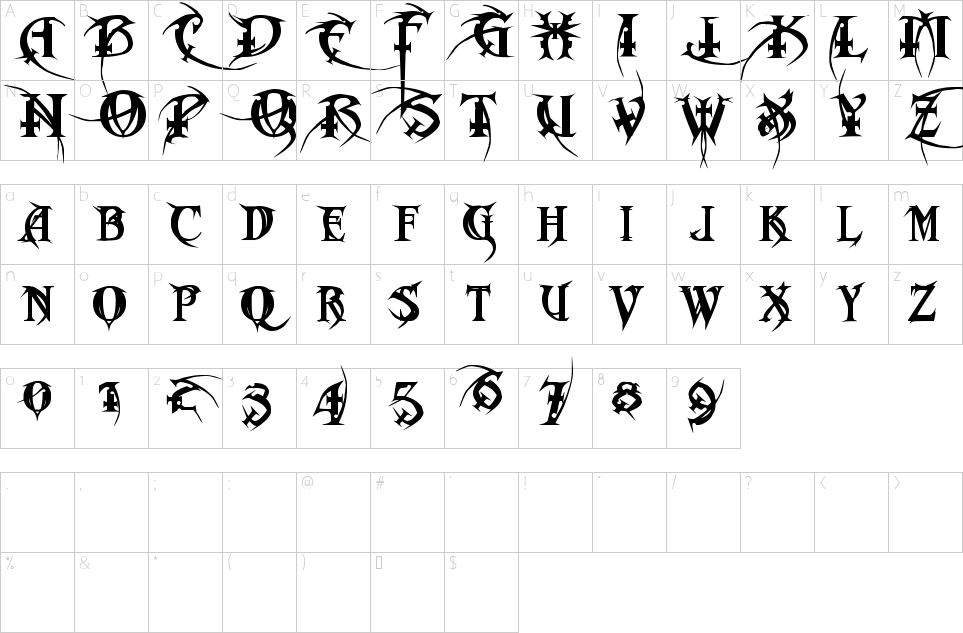
Descubra a beleza sombria e a força inigualável da Metal Macabre font. Desenvolvida por Bolt Cutter Design, esta elegante fonte se encaixa perfeitamente para criar um estilo macabro e emocionante nos teus trabalhos digitais. Com sua aparência agressiva e detalhes carregados, a Metal Macabre é uma escolha ideal para ambientes onde a temática metalica e macabra são fundamentais. Seja para títulos de revistas de metal pesado, nomes em selos de discos ou até mesmo como letras de música, a Metal Macabre oferece o poder necessário para expressar seu próprio gosto. Descubra agora e adicione a sua coleção de fontes gratuitas com a Metal Macabre, uma escolha inteligente para qualquer designer.